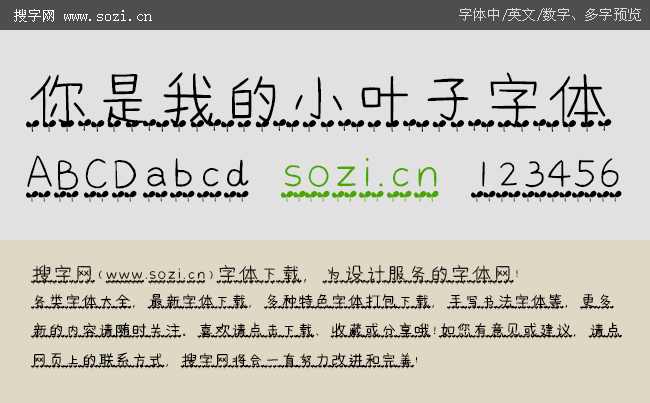
你是我的小葉子字體
搜字網(wǎng)給大家提供一款很卡通的手機(jī)中文字體下載。修改者將它命名為你是我的小葉子字體,這款手機(jī)字體是仿照兒童手寫(xiě)風(fēng)格的卡通手寫(xiě)字體,結(jié)構(gòu)帶有POP字體風(fēng)格,字體下面還配上了非常有趣的卡通圖案做襯線(xiàn),特別適合喜歡手機(jī)字體個(gè)性一些的朋友在手機(jī)上安裝使用。